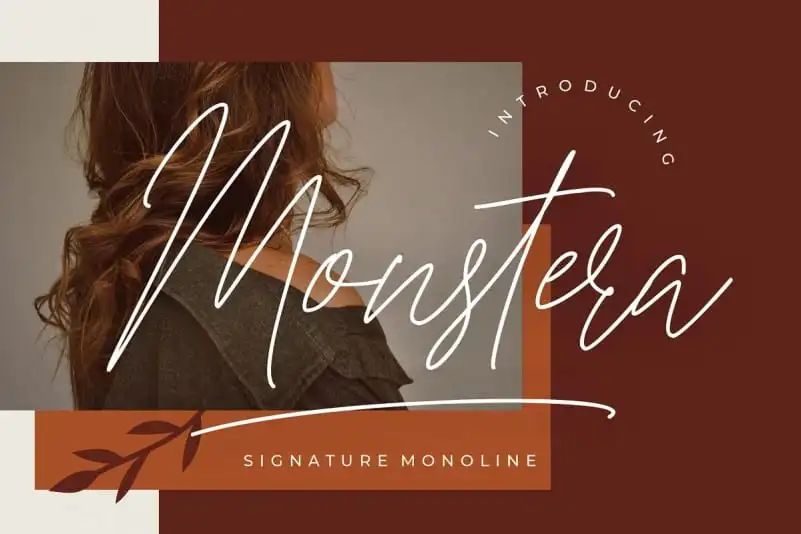
Monstera Handwritten Font – Download Grátis
A Monstera Handwritten Font é uma fonte de签字精心手工绘制而成,使用了钢笔书写并数字化重现。它专为品牌项目、标志设计、婚礼布置、社交媒体帖子、广告宣传、产品包装、产品设计、标签、摄影、水印、请柬和信纸等多用途项目打造,赋予作品一种手写特有的优雅与个性。不论是在日常生活的点滴还是在重大活动的时刻,她都能让您的创作散发独特的魅力。无论是为一个新品牌寻找独一无二的声音,还是希望给客户留下深刻印象的设计项目,这款字体都是一个理想的选择。不妨将它融入到您的设计中,享受那份手写带来的独特韵味吧。